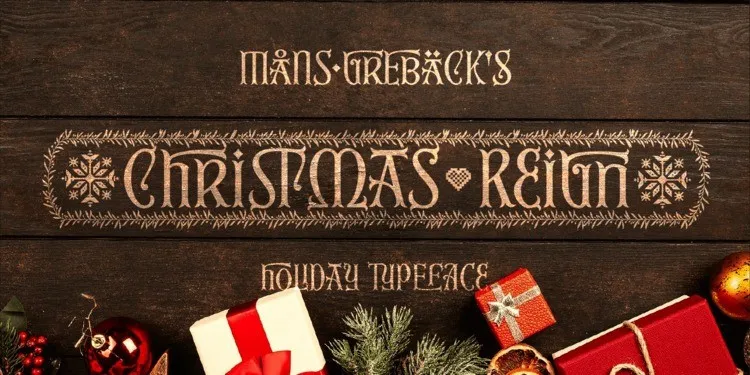
A Christmas Reign Display Font é uma fonte moderna que combina características clássicas com técnicas vintage de letra à mão. Desenvolvida pelo designer Mans Greback através do 99designs, essa fonte apresenta um estilo único e vibrante, combinando elementos tradicionais com a atualidade de formas modernas. Ideal para decorar cartões de Natal, adesivos personalizados, posts nas redes sociais ou qualquer tipo de decoração que você possa imaginar, esta fonte oferece uma variedade única e intrigante. Os detalhes de cada letra parecem vivos, como se fossem um doodle criativo à mão. Tente a Christmas Reign Display Font e descubra como as combinações de letras podem criar novas formas, tornando-as perfeitas para dar vida às suas ideias mais fantásticas.